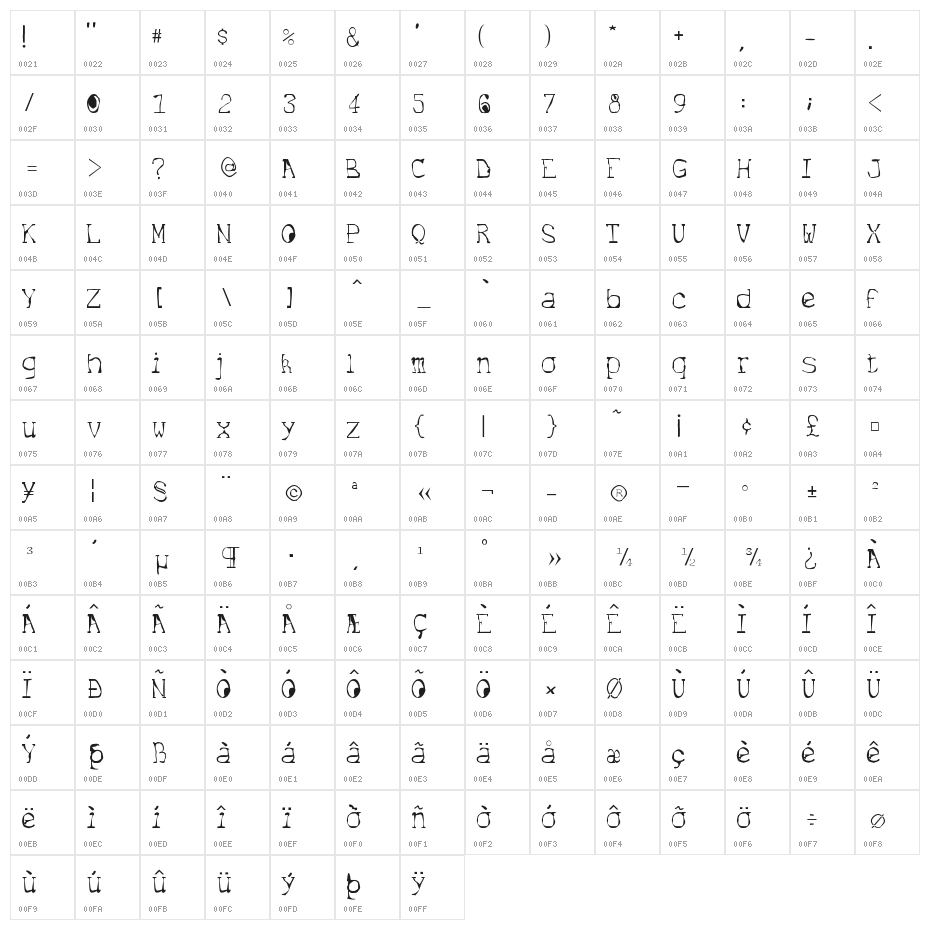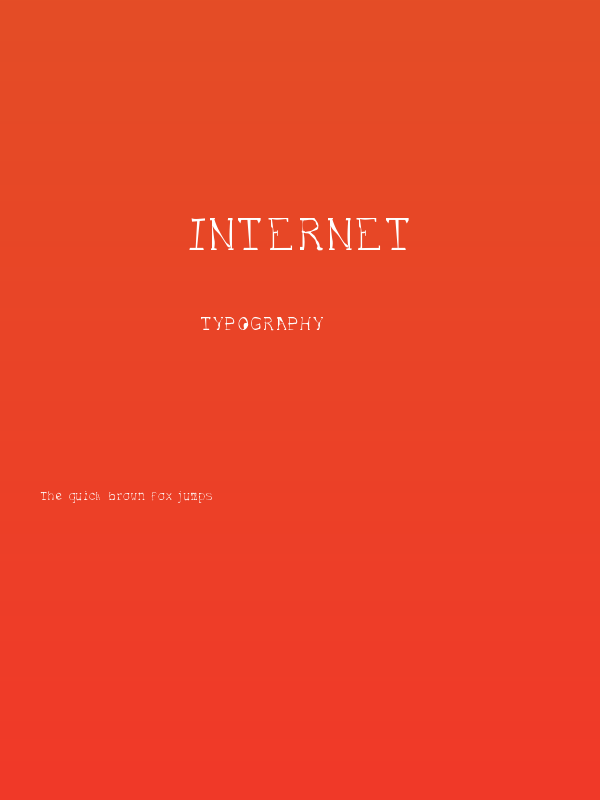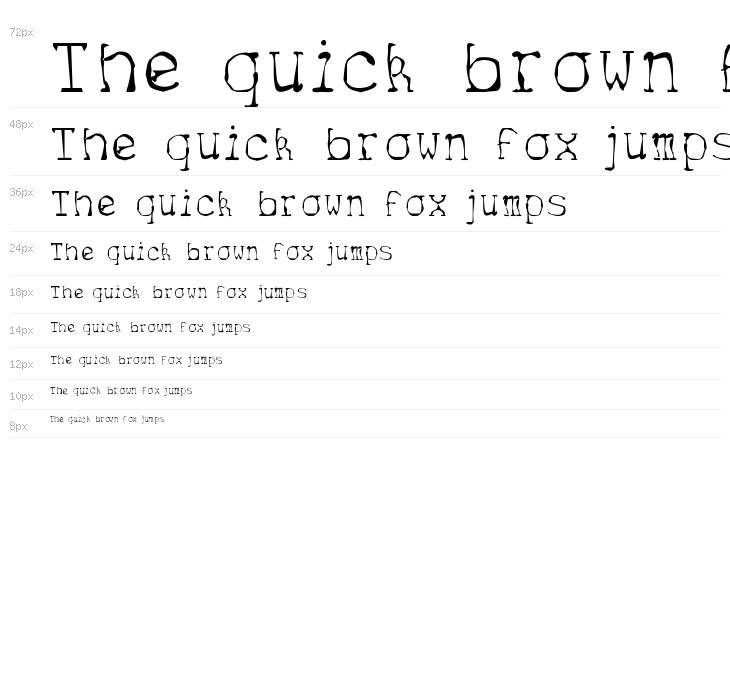
Internet Font
| Estilo general | Artistic and playful |
| Caso de uso | Headlines, Artistic projects, Branding |
| Proyectos propuestos | Ideal for creative projects such as posters, album covers, children's books, and artistic branding. |